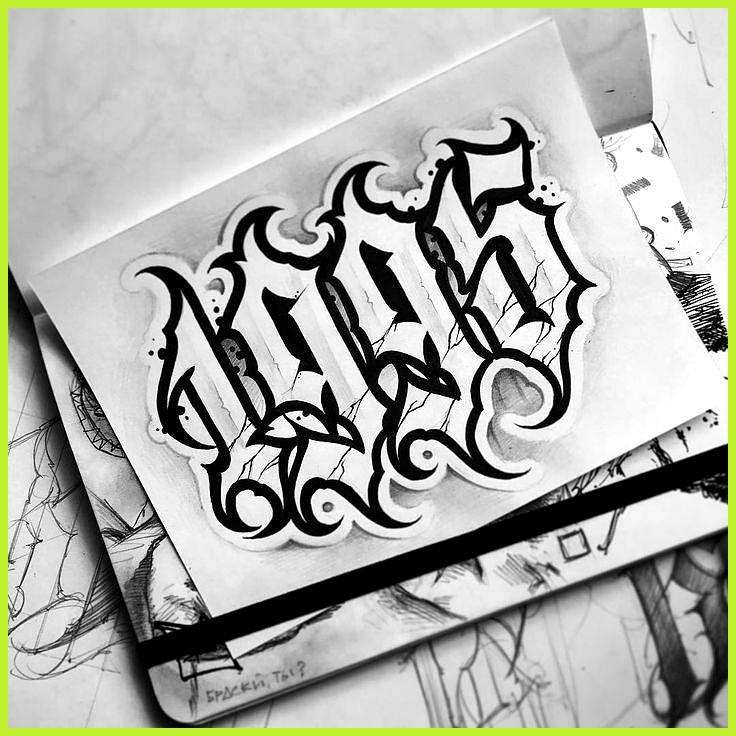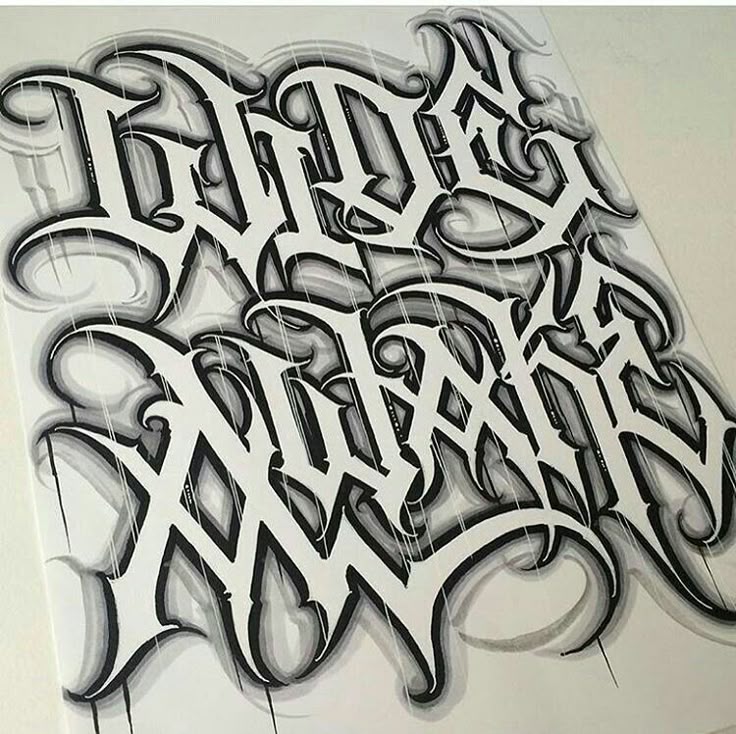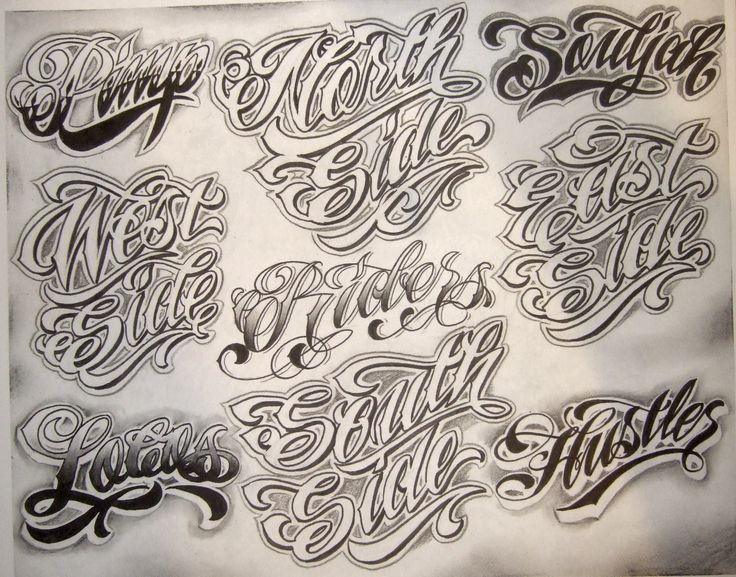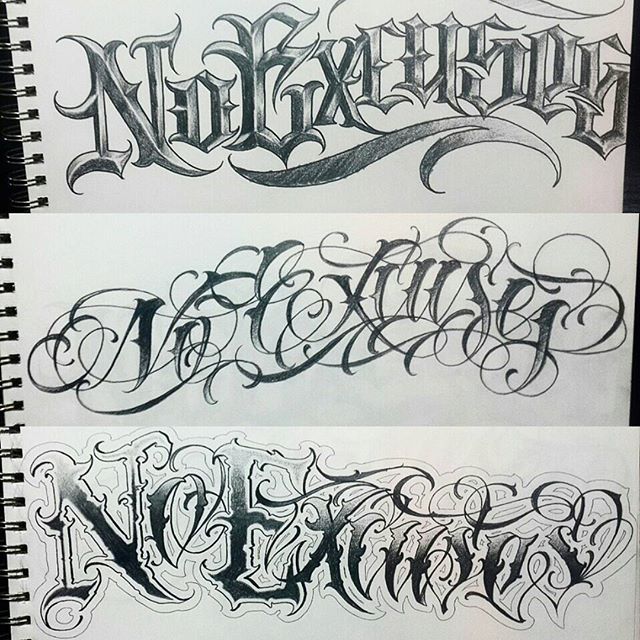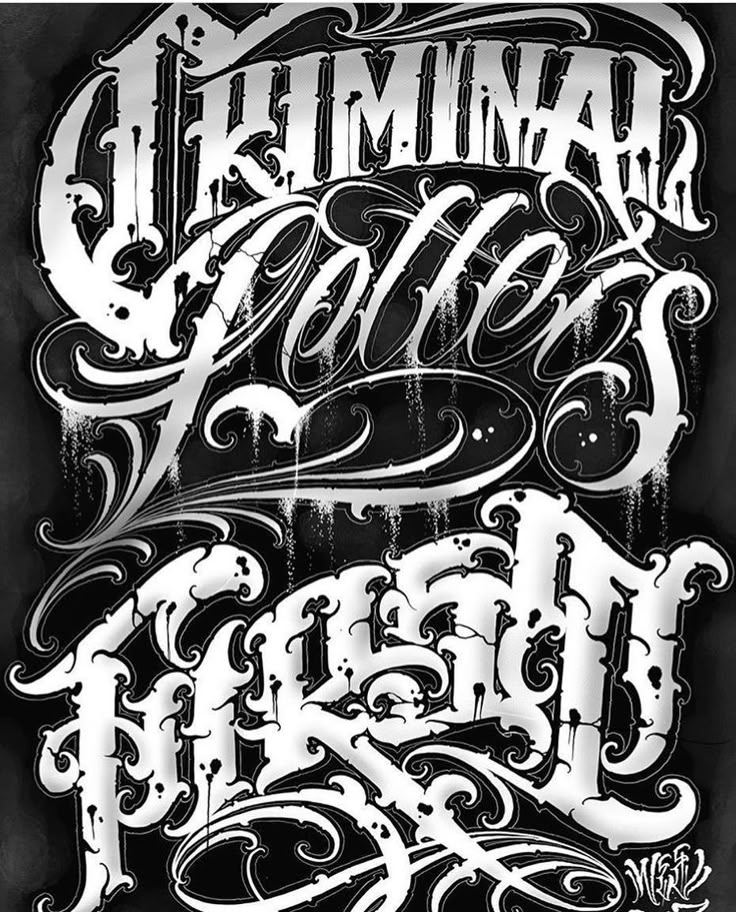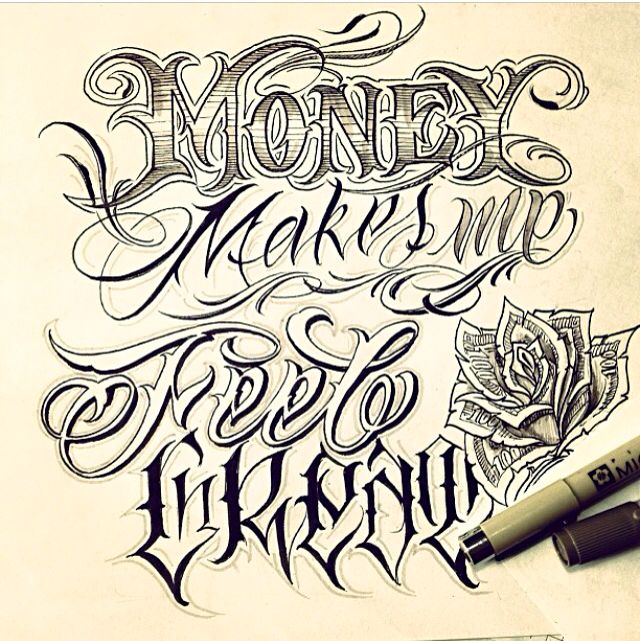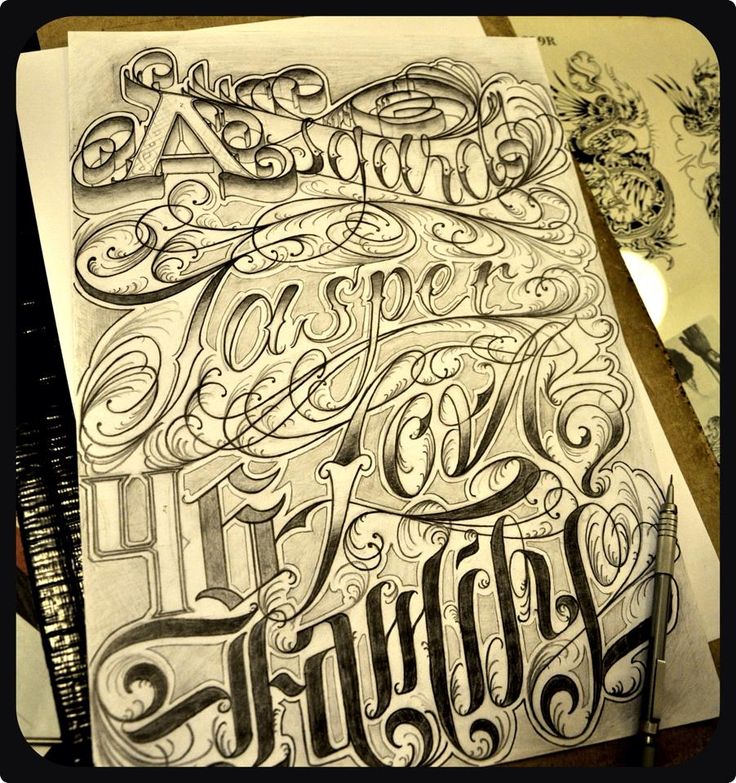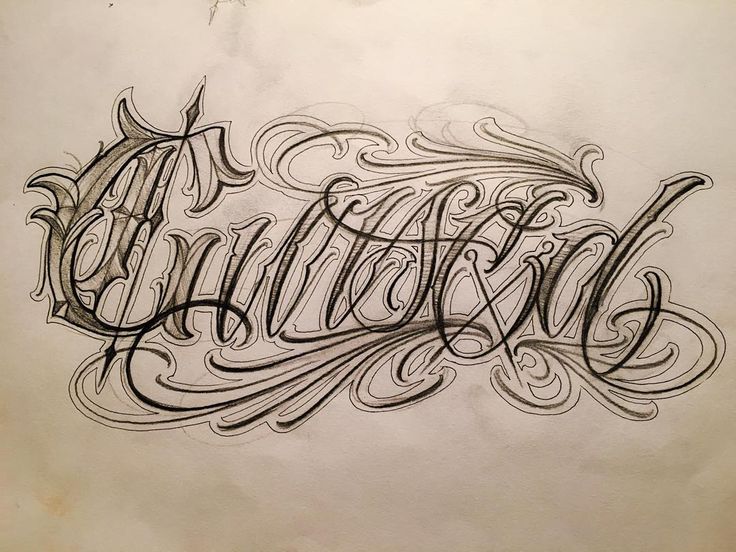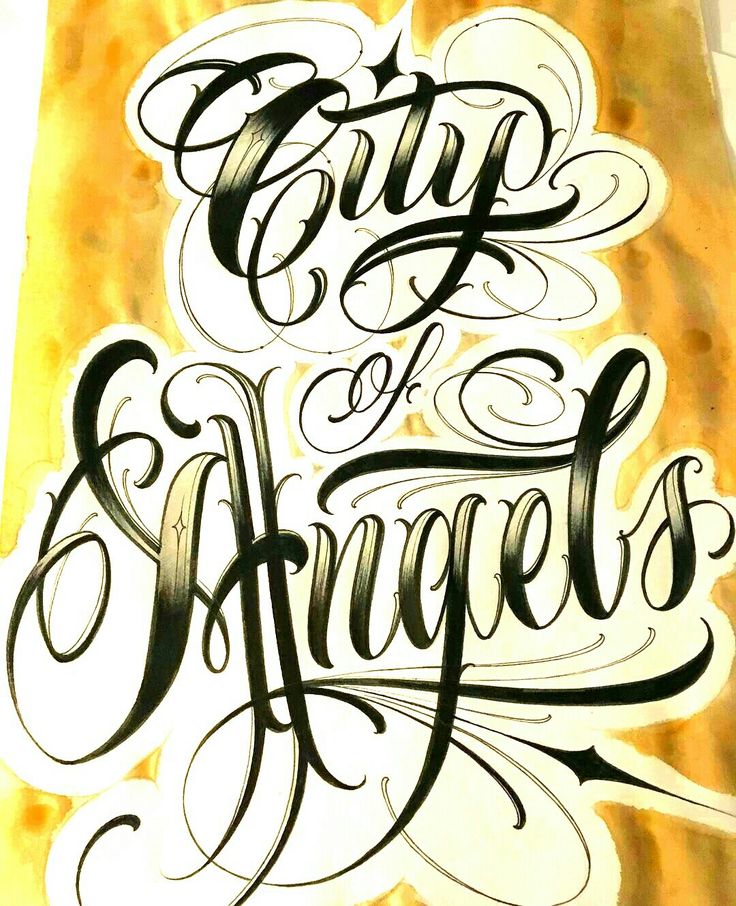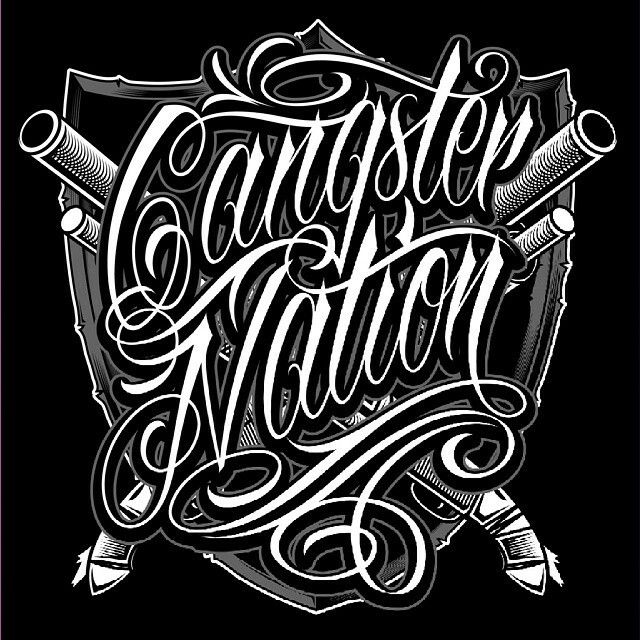
Рукописный
Наиболее важной чертой почерка является небрежность. Каждый почерк имеет уникальный стиль и штрихи. Некоторые предпочитают четкость между словами, но некоторые люди также любят персонализированные рукописные шрифты.
Нанести на тело почерк важного для себя человека, что может быть романтичнее этого?
Большинство почерков выполнены мягкими штрихами, чтобы создать ощущение легкости.